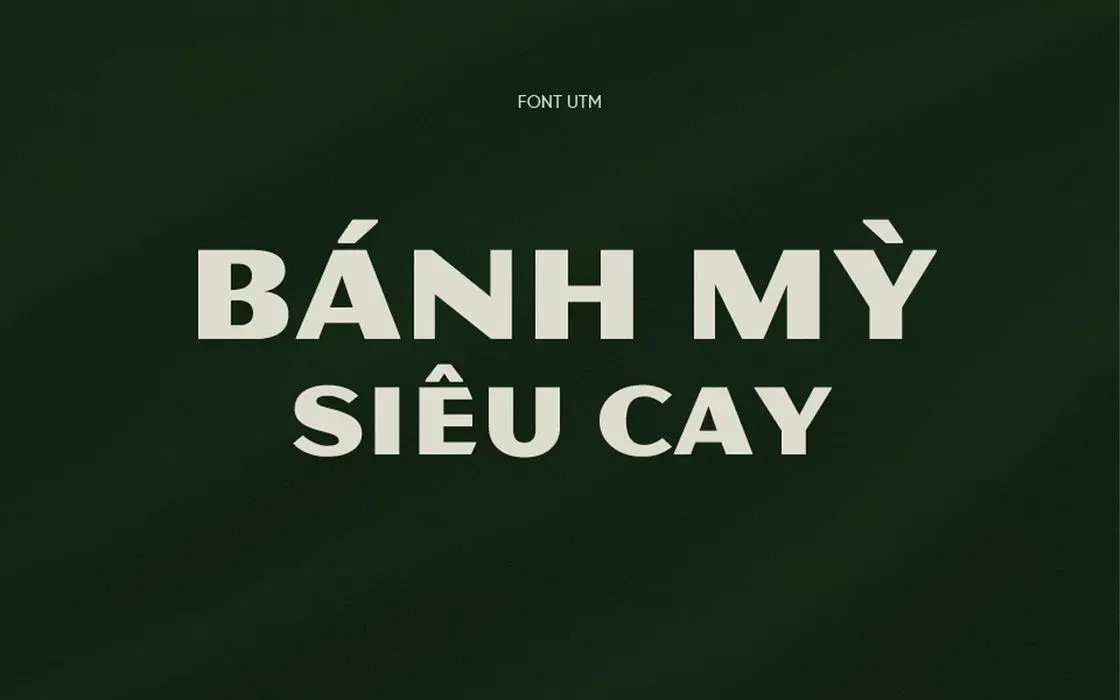
UTM Magnesium là một kiểu font sans-serif mạnh mẽ, nổi bật với thiết kế chữ to bản, đường nét dứt khoát và hình khối chắc khỏe. Mỗi ký tự trong font mang dáng vẻ vuông vức, vững chãi, với các nét thẳng và bo góc tinh tế giúp tăng tính dễ đọc nhưng vẫn giữ được sự cứng cáp đặc trưng. Font này đặc biệt lý tưởng cho những thiết kế cần thể hiện sự chuyên nghiệp, rõ ràng và hiện đại – như poster sự kiện, banner quảng cáo, slide thuyết trình, hay logo thương hiệu công nghệ.
UTM Magnesium tạo cảm giác rất "công nghiệp" và "kỹ thuật số", thích hợp với các dự án truyền thông mạnh về visual impact (tác động thị giác). Dù có kiểu dáng đơn giản, nhưng font vẫn giữ được sự ấn tượng và mạnh mẽ, giúp thu hút sự chú ý từ người xem.
Font gốc Magnesium được thiết kế bởi một tác giả quốc tế (hiện chưa công bố rõ ràng), thường được sử dụng như một kiểu chữ tiêu đề hoặc headline trong các bản thiết kế hiện đại. Bản Việt hóa được thực hiện bởi nhóm Urban Type Management (UTM) – đơn vị uy tín tại Việt Nam chuyên Việt hóa font chữ với đầy đủ dấu tiếng Việt và tinh chỉnh kỹ lưỡng để đảm bảo tương thích với nhiều phần mềm như Photoshop, Illustrator, Canva...
Với sự cứng cáp, mạnh mẽ và dễ sử dụng, UTM Magnesium là lựa chọn hàng đầu cho các nhà thiết kế đang tìm kiếm một font chữ sans-serif chuyên nghiệp, rõ ràng và tạo điểm nhấn mạnh trong các thiết kế thương hiệu, kỹ thuật hoặc truyền thông thị giác.